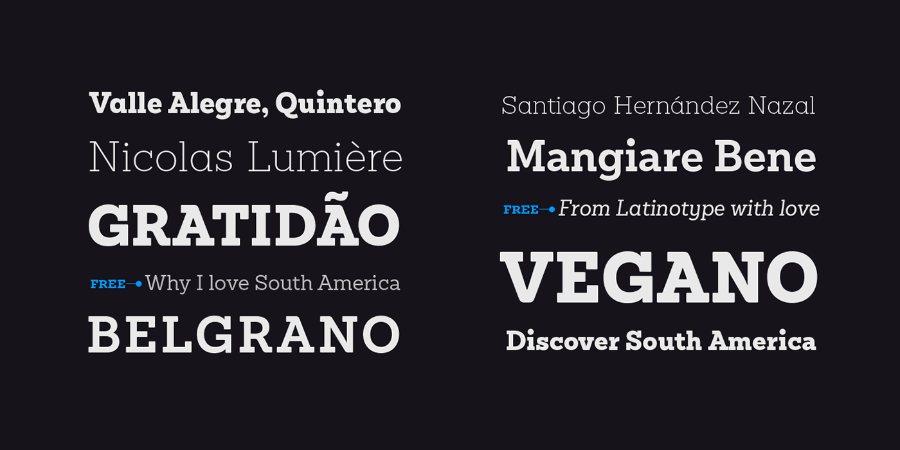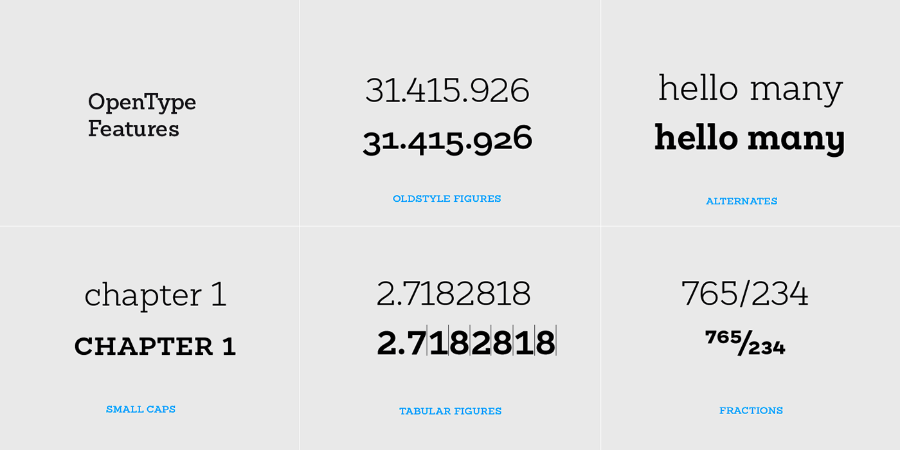
桑切斯牛免费演示在这里!这个系列是对2011年Latinotype推出的首批字体系列之一Sánchez的重新设计。这个新版本包括了一些改进,使其能够很好地处理较长的文本。现在,它有了一些新的字符以及OpenType功能,如小大写字母和风格替代。桑切斯牛包含一组720个字符,支持219种语言。该字体适用于长文本、标题和标识。此外,它还针对web使用进行了优化。此外,César Araya、Rodrigo Fuenzalida和Alfonso García的更正、数字编辑和评论。